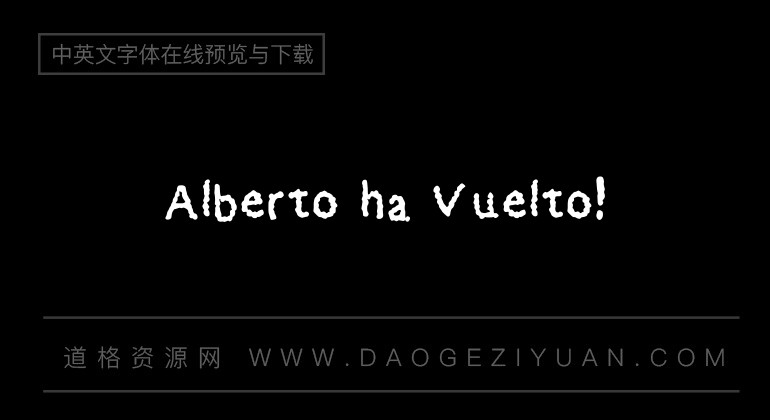
Alberto ha Vuelto!
Alberto ha Vuelto! 是一款字体,由西班牙设计师 Alvaro Arranz 创作。这款字体融合了现代设计手法与传统西班牙风格,是一款拥有独特魅力的字体。它具有优雅的外观和舒适的感觉,能够轻松地为您的设计作品增添一份优雅和浪漫气息。Alberto ha Vuelto! 字体具有多种字体风格,包括正常、斜体、粗体、细体等,可以满足您的不同需求。
Alberto ha Vuelto!是一款非常不错的手写艺术字体,具有很好的视觉感,适合于文化类的宣传设计、商业类品牌的广告和产品包装设计以及个性化文字排版等较多场景。